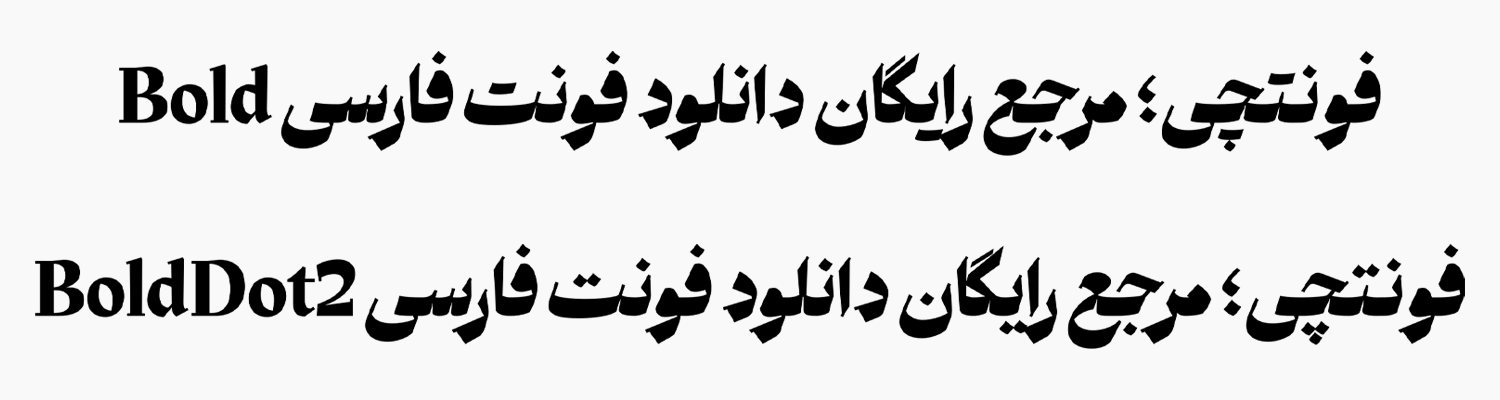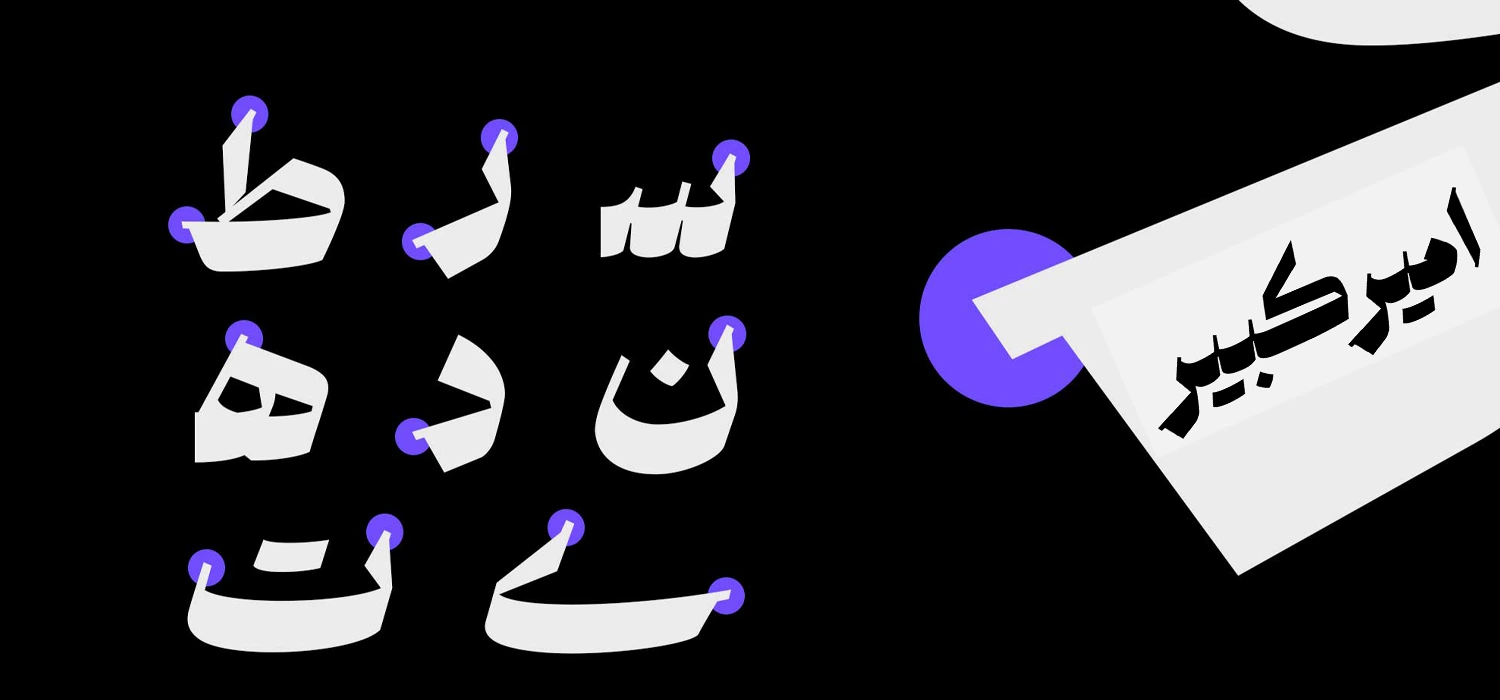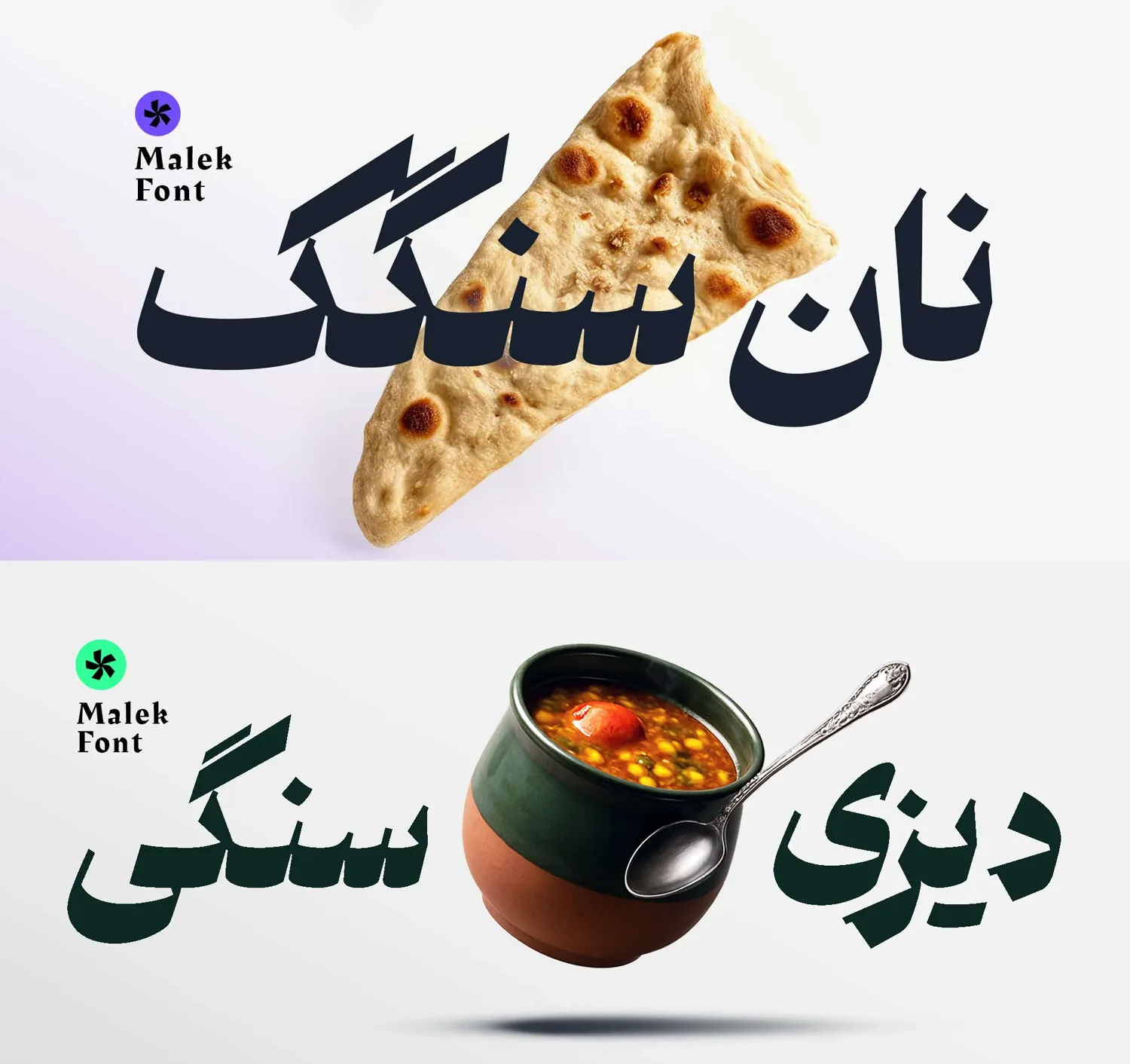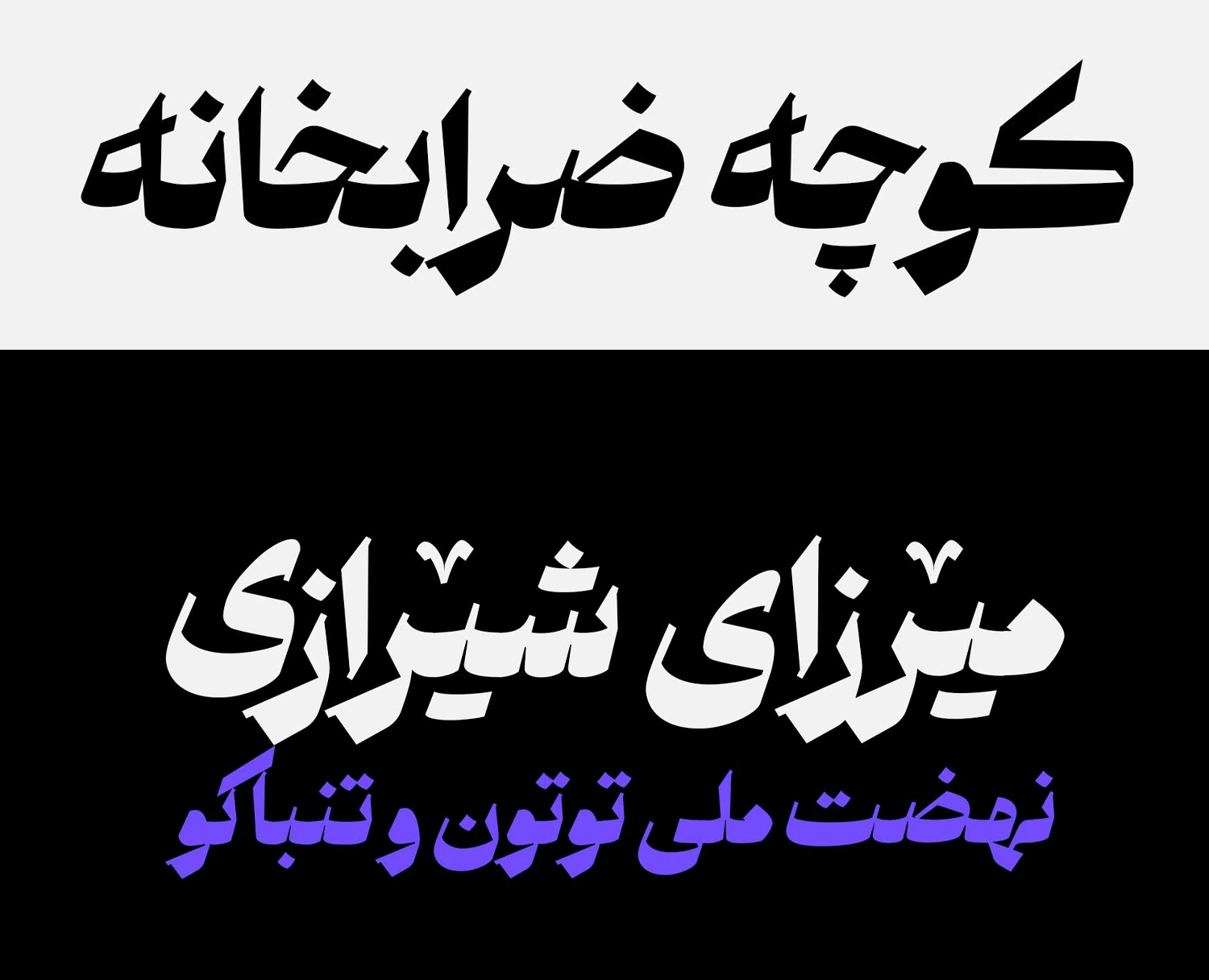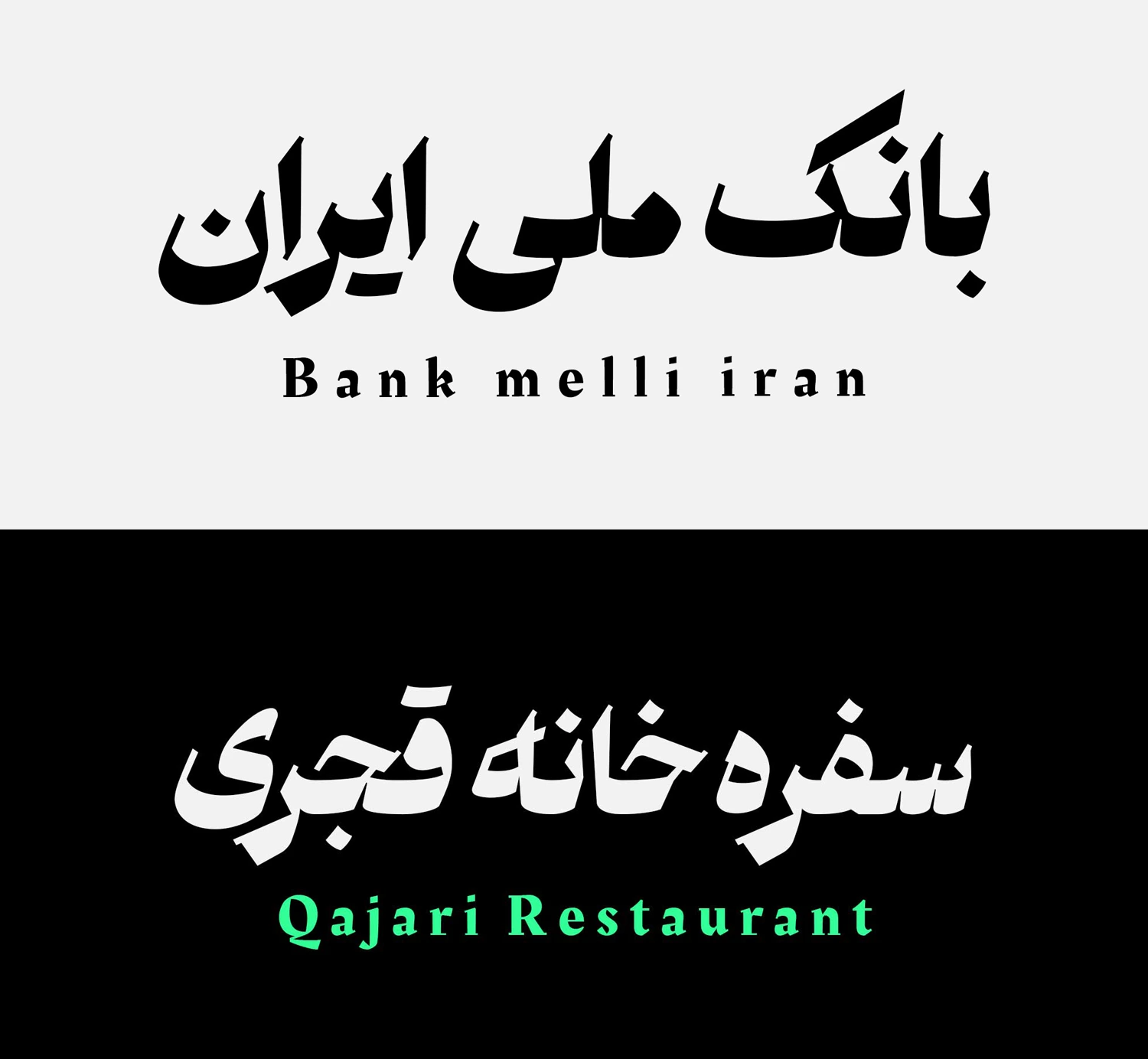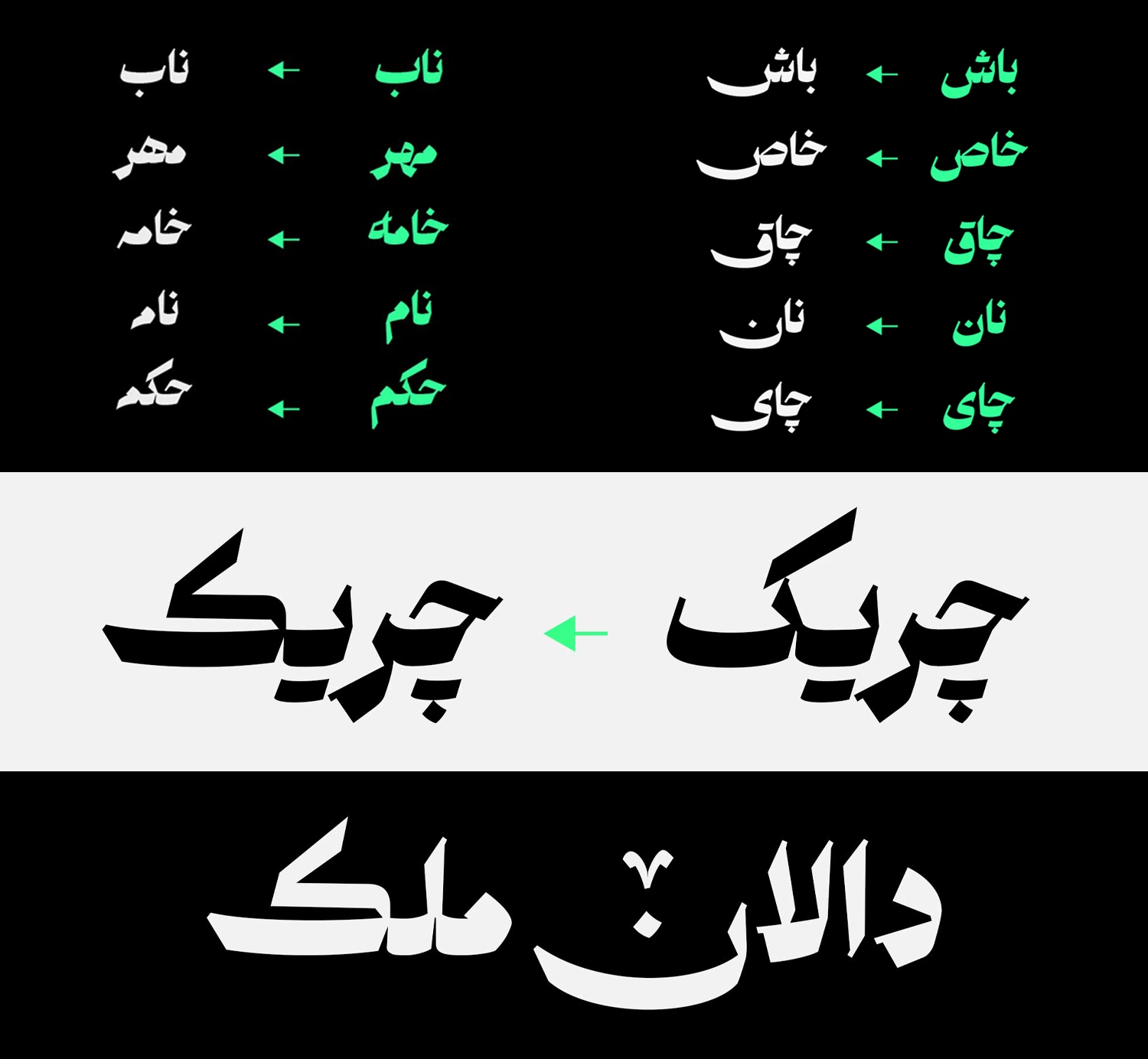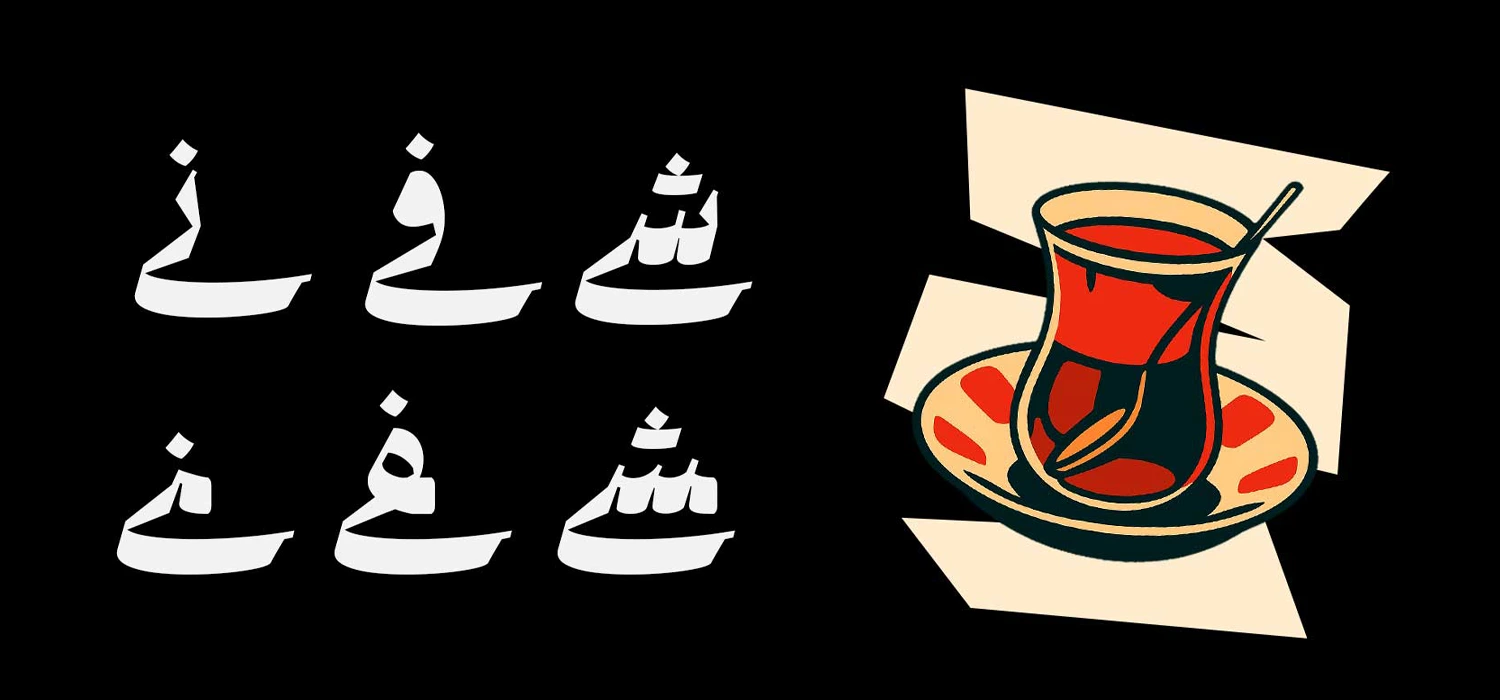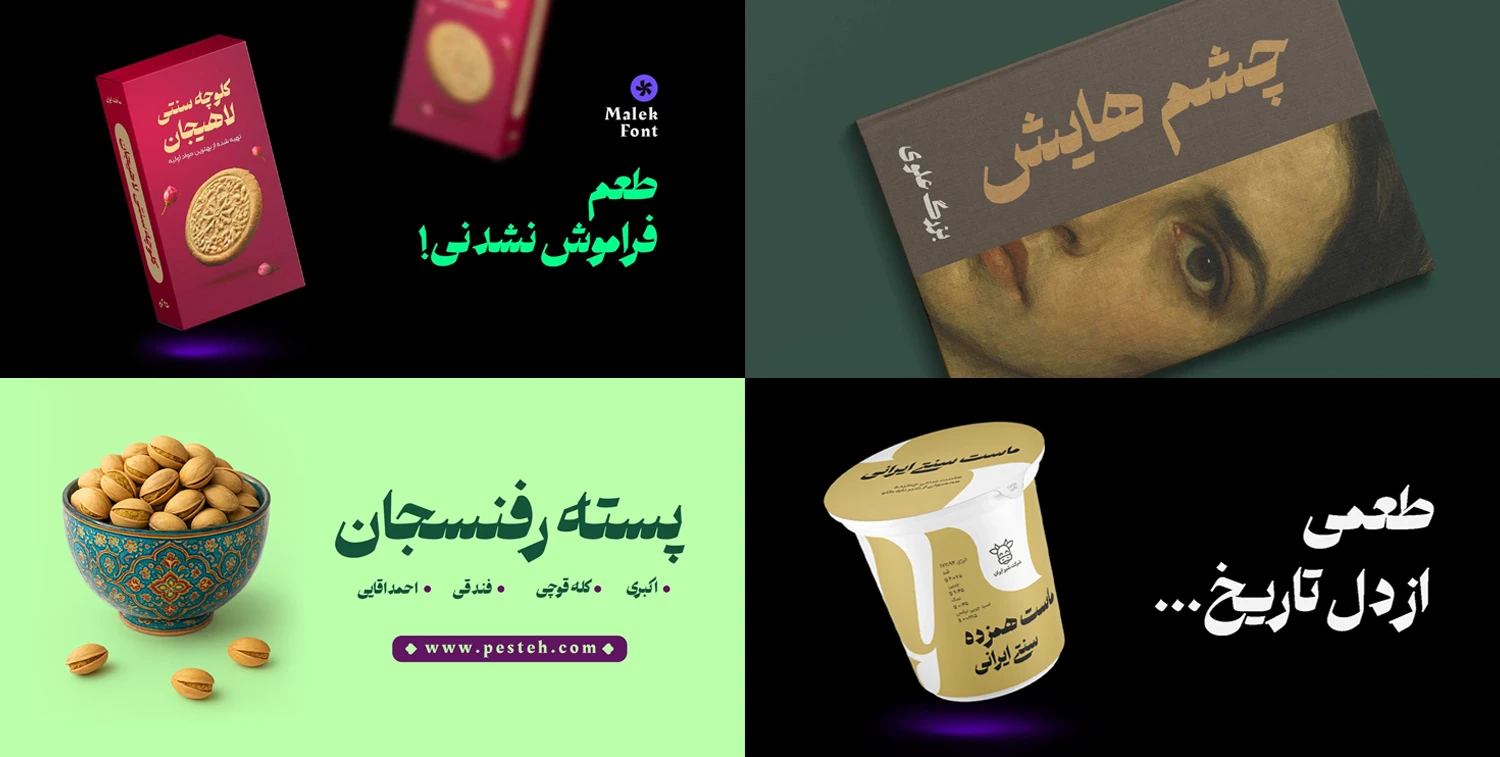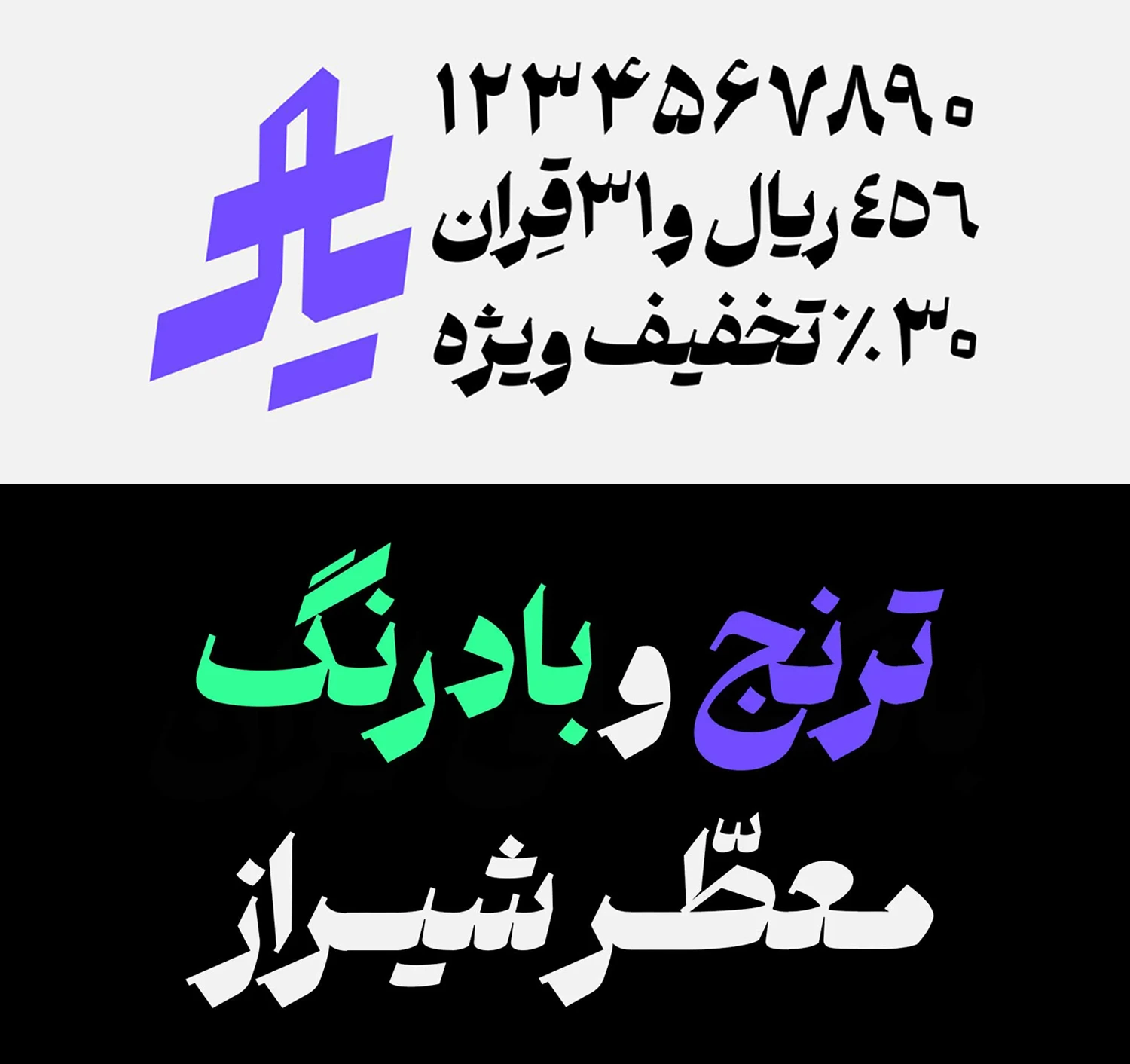
فونت ملک (Malek)
| نام | ملک |
| نام نمایشی | Malek |
| طراح | رضا بهلول، سید مهدی سیدی نیا |
فونت ملک (به انگلیسی: Malek) ریشه در سنتهای خطاطی ایرانی دارد و ترکیبی هوشمندانه از ساختار هندسی «نسخ» (با نظم و ثبات) و سیالیت «نستعلیق» (با انحناهای ظریف و پویا) است. انحناهای نرم در کنار شکستهای زاویهدار، حس اصالت و وقار را با مدرنیته آمیخته است.
سید مهدی سیدینیا این فونت را با شرکت در دوره تایپتراپی مسلم ابراهیمی طراحی نموده که تلاش میکند شکاف میان خطاطی سنتی ایرانی و نیازهای گرافیک معاصر را پر کند. توسعه فونت نیز توسط رضا بهلول انجام گرفته که پیش از این آثار مختلفی از وی را در سایت فونتچی منتشر نمودهایم.
با توجه به ساختار هندسی و تمرکز روی خوشنویسی اصیل ایرانی فونت ملک و وزن بولد که این فونت دارد میتوان از آن در کارهایی که جنبه نمایشی دارد استفاده کرد. عناوین کوتاه، شعارهای تبلیغاتی، جلد عنوان کتاب و مجلات از رایجترین کاربردهای این فونت است. در ادامه به نقد و بررسی کامل این فونت فارسی و کاربردهای بیشتر آن میپردازیم.
دانلود فونت ملک (Malek) مناسب عناوین و تبلیغات
سبک طراحی فونت ملک امروزی و مدرن است. این فونت فارسی دارای ساختاری از خط خوشنویسی اصیل ایرانی است که با استفاده از زوائد و منحنیهای جهتدار تزيین شده و حس وقار به آن داده شده است.
برای مثال، در حروفی مانند «ب، ن، م، خ، ح» زوائدی در انتهای حروف قرار داده شده که علاوه بر برجسته کردن فونت، ظاهر ان را مدرن، نمایشی و امروزی میکند. در پروژههایی با هویت فرهنگی ایرانی مانند پوسترها، جلد کتابها یا هویت بصری برندها چنین ساختاری حس خاصی را به مخاطب القا میکند.
ترکیب این فرمهای منحنی در کنار زوایای تیز که با هدف پویایی استفاده شده، انعطاف این فونت را خاص کرده است. بهویژه اینکه فونت از دو سبک وزنی پشتیبانی میکند. علاوه بر نسخه بولد فونت ملک یک نسخه هم با سبک نقطهگذاری منفصل وجود دارد که به انتخاب خود میتوانید از دو سبک استفاده کنید.
فونت فارسی ملک محدود به این زبان نبوده و از زبان عربی با حفظ تمامی استانداردهای حروف نظیر اعراب، اعداد خاص عربی «٠٤٥٦» و کاراکترهای خاص پشتیبانی میکند. تمامی این کاراکترها در هر دو زبان با چینش مناسبی در کنار هم قرار گرفته و ساختار این فونت نمایشی را تکمیل میکند.
علاوه بر این فونت از زبان انگلیسی نیز پشتیبانی میکند. اما بهجای اینکه از همان سبک به صورت اختصاصی استفاده شده باشد، از یک فونت با لایسنس رایگان بهره برده شده است که نزدیکی بسیار خوبی به این قلم دارد.
حروف جایگزین و ترکیبات خاص
یکی از نقاط قوت فونت ملک پشتیبانی از حروف جایگزین یا همان Alternatives است. به کمک این ترکیبات جایگزین میتوانید برخی حروف خاص مانند «س، ش، ص، ض، ن، ی» یا ترکیبات خاصی مثل «ـشی، ـسی، ـفی، ـنی، ـم، ـمه، ـر، ـز» را به شکلی متفاوت تایپ کنید.
تایپ این حروف جایگزین باعث ایجاد تفاوت در ساختار تایپ کلمات میشود که ناخودآگاه با ایجاد یک ناهمانگی در بین دیگر کلمات، باعث درگیری ذهن مخاطب و جلب توجه وی خواهد شد. علاوه بر این میتوانید با استفاده از این فونت در برنامههای گرافیکی نظیر فتوشاپ به سادگی کارهای گرافیکی خلاقانه انجام دهید؛ بدون اینکه نیاز باشد ساعتها از نرمافزارهایی مثل ایلاستریتور استفاده کنید.
در کنار این حروف جایگزین امکان تایپ کاراکترهای تزئینی که بیشتر در زبانهای کردی و اردو آنها را دیده ایم فراهم است که در کارهای فرهنگی و هنری میتواند به منظور زیبا سازی کارها مورد استفاده قرار گیرد. با چنین ساختاری میتوان انتظار داشت که پشتیبانی کاملتر و استانداردتر این قلم از این زبانها نیز در آینده افزوده شود.
فونت ملک انتخابی عالی برای فارسی زبانان
این فونت فارسی خلق شده تا حروف فارسی را در بخش عناوین و متون کوتاه دگرگون کند. همانطور که ذکر شد استفاده از این فوت برای عناوین، تبلیغات و به طور کلی متون کوتاه انتخابی عالی است. خصوصا وقتی هدف جنبه شعاری داشته باشد که در ابعاد بزرگ از این فونت استفاده کنید.
زوایا، زائدهها و منحنیهایی که با هدف ایجاد سیالات خاص در این فونت پیاده شده بیشتر و بهتر دیده شده و ساختاری صمیمی را با مخاطب برقرار میکند. در کنار آن حروف جایگزین و استفاده از کاراکترهای تزئینی نیز روی این مسئله تاثیر میگذارد.
در بسته دانلود فونت ملک شاهد نسخهای هستیم که علاوه بر اعداد استاندارد فارسی و عربی، گلیفهای خاصی همچون ریال را نیز در خودر دارد. این گلیف برای کارهای تبلیغاتی، بهویژه بیلبوردهای درون شهری یا تابلوهای سردر مغازهها انتخاب خوبی است که میتواند مخاطب را جذب کند.
کاربردهای فونت نیز علاوه بر عناوین میتواند در شبکههای اجتماعی یا رسانههای ویدئویی به منظور ساخت تامنیل یا کاور پستها مورد استفاده قرار گیرد. خصوصا با وزن بولدی که دارد جلب توجه کرده و نرخ کلیک را افزایش خواهد داد.
جدیدترین نسخه فونت ملک با شماره ۱.۰ در آبان ۱۴۰۴ در قالب بستهای دو وزنی شامل نسخه Bold و نسخه بولد با سبک نقطهگذاری ناپیوسته طراحی شده است. در این نسخه شاهد پشتیبانی کامل از زبان فارسی و عربی در کنار ساختار اپنسورس برای زبان انگلیسی هستیم.